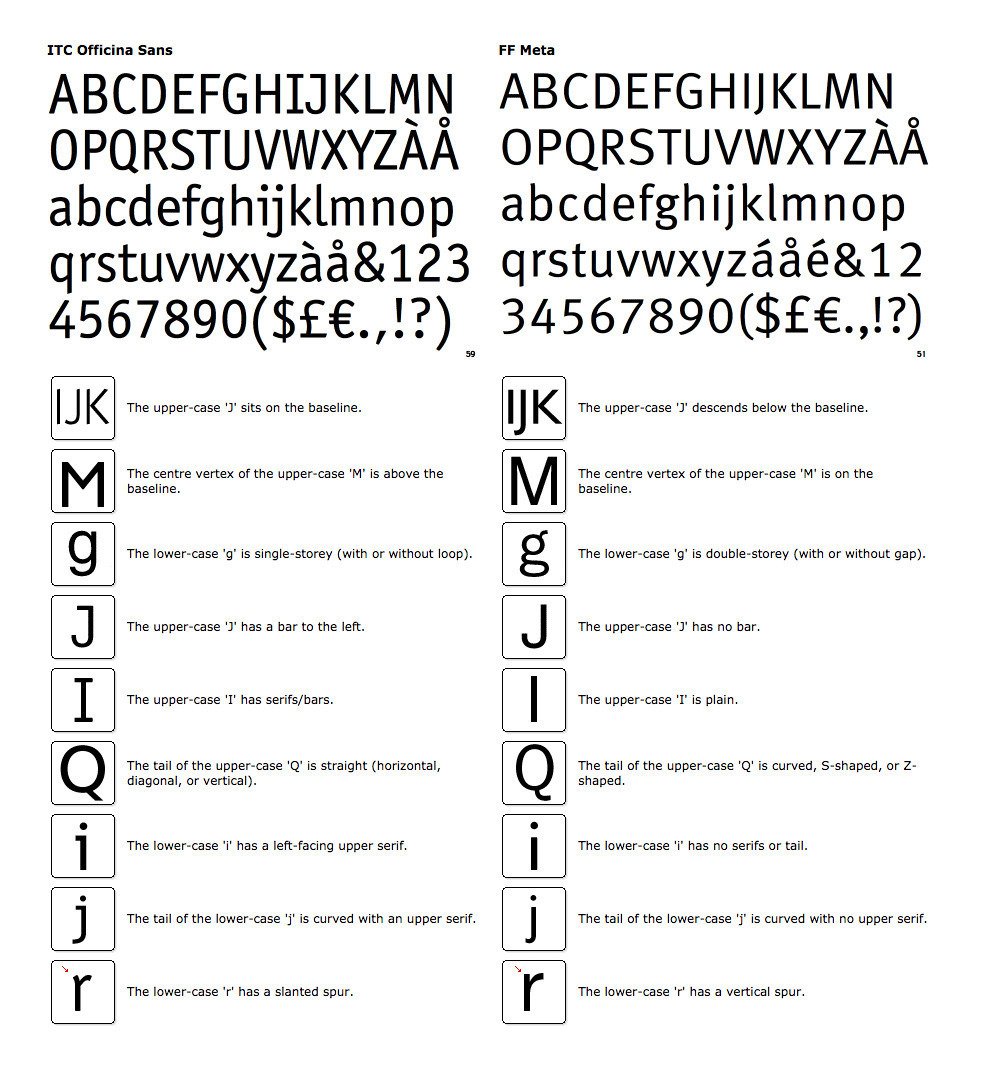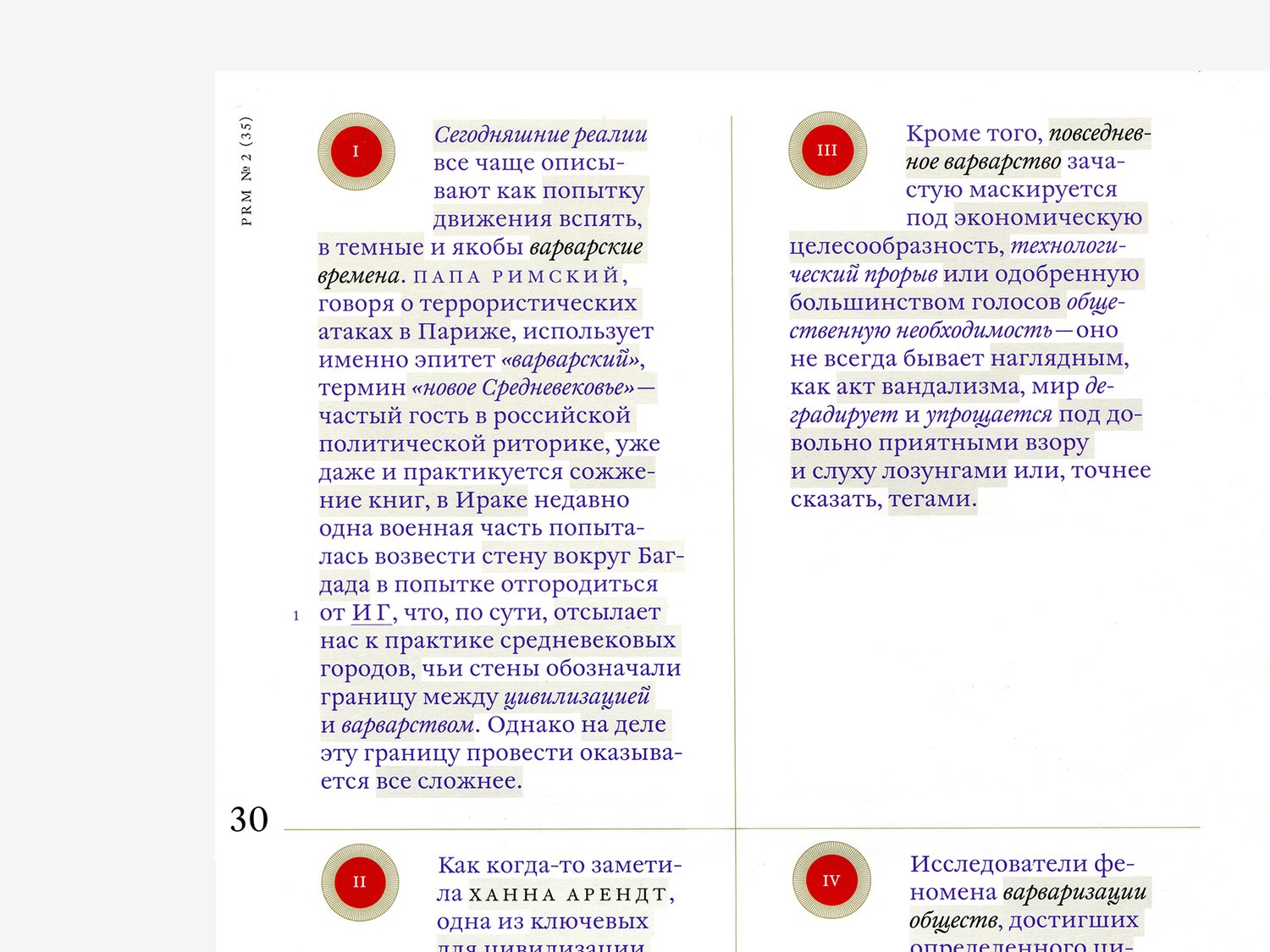
Shuka — одна из самых ярких дизайн-студий страны. Мы поговорили с со-основателем студии Иваном Величко о современном состоянии графического дизайна, швейцарской крови и реальности.
Илья Рудерман: Что для тебя шрифт сегодня?
Иван Величко: Странное дело, но сегодня все вокруг говорят о шрифтах. Шрифт стал какой-то модной темой для обсуждения, а для многих молодых дизайнеров — просто каким-то мистическим космосом, магией. Но мне кажется, что весь этот шум мы сами и создаём, мы сами искусственно вывели эту тему в топ.
Я, честно говоря, не вижу тут какого-то отдельного предмета для долгого обсуждения. Шрифт для меня — это всё-таки прежде всего инструмент. Я сам этим инструментом постоянно пользуюсь, с удовольствием могу порассуждать — какой шрифт мне больше нравится, какой меньше и почему, но не стоит устраивать из этого дискуссии планетарного масштаба.
На мой взгляд, проблема современного графического дизайна состоит в том, что для него ещё не придумали адекватного языка. Взять, например, другие профессии: в кино последние полвека все лучшие фильмы снимаются о том, как делать фильмы; театральные спектакли ставятся о том, что такое театр в наше нелёгкое время. А дизайн этой рефлексии избежал, у нашей профессии пока не появилось собственного понятийного аппарата. Поэтому всерьёз об этом рассуждать мы не умеем, у нас просто пока нет терминов.
ИР: Ты начал с того, что шрифт, в общем-то, микроскопическая история, недостойная серьёзного обсуждения, а закончил тем, что на самом деле проблема в отсутствии словаря для обсуждения графического дизайна и шрифтов. А как сегодня твоё общение со шрифтом — его использование и восприятие — отличается от того, что было, допустим, два года назад?
ИВ: Мой дизайн очень сильно связан с тем, из чего я его делаю. В своих работах мы часто используем то, что сами рисуем, графику, произведённую если не в стенах студии, то нашими друзьями или художниками, с которыми мы работаем. Шрифт — это большое количество чужой графики в макете, очень много графики, нарисованной каким-то другим художником. Много просто по площади, которую этот элемент занимает. И эта чужая графика очень сильно влияет на интонацию произведения, на то, как ты это делаешь, на то, как тебе с этим работается. Есть шрифты, с которыми нужно находить общий язык, есть шрифты, с которыми тебе просто некомфортно, есть шрифты, которые тебе ниспосланы провидением.
Сайт дизайн-бюро «Щука». На сайте используется специальная версия шрифта Gerbera вместе с безымянным гротеском Ивана Величко
Сайт дизайн-бюро «Щука». На сайте используется специальная версия шрифта Gerbera
У меня был опыт работы с Судостроительным банком («СБ Банк»). Они пришли и к нам в 2008 году со словами: «Наш фирменный шрифт — Officina». В 2008 году Officina выглядела анахронизмом из 2001 года. И я подумал: какой ужас, придётся иметь дело со шрифтом Officina. Однако поработав с ним какое-то время, я понял, что из него, вообще-то, можно вытащить совсем другие свойства, не те, что вытаскивали создатели брендбука в ранние 2000-е. Я придумал, как с ним сделать вполне модернистские композиции, как превратить его в модную историю.
ИР: С каким модным шрифтом тебе было некомфортно работать?
ИВ: С Meta. С «Метой» было сложно ещё и потому, что у него много начертаний. А по моим ощущениям, у шрифта есть ровно одно начертание, с которым мне комфортно, все остальные мне просто не нужны.
Сравнение шрифтов Officina Sans и Meta на сайте Identifont
Например, сейчас мы набрали сайт шрифтом Gerbera, который сделала Гаянэ (Гаянэ Багдасарян и Вячеслав Кирилленко — авторы шрифта Gerbera. — Прим. ред.), но мне для этого пришлось потрудиться, я везде поставил альтернейты, какие мне хотелось, попросил Гаянэ сделать специальный файл, и мы использовали только Medium.
ИР: Твои представления о шрифте по дефолту как-то менялись? Например, у тебя был период любви к одному шрифту, потом ты увлёкся другим? И какой дефолтный шрифт у тебя сейчас?
ИВ: Когда мы начинали делать многостраничные издания, у нас по дефолту стоял Charter, почти всегда. После Charter мы стали везде ставить William, который мой шрифт по умолчанию до сих пор.
Дизайн журнала The Prime Russian Magazine со шрифтом William
ИP: Мне нравится, что у тебя шрифты по дефолту — антиквы. А какой-нибудь гротесковый дефолт есть?
ИВ: Раньше я ставил Circe, они с «Вильямом» хорошая пара. Есть, правда, ощущение, что с Circe сегодня в городе небольшой перебор. И он сложноват для дефолтного шрифта. Но сейчас у меня новый любимый гротеск — Figgins.
Шрифт Figgins Sans дизайнера Ника Шина (Nick Shinn)
Чехословацкий трёхтомник Олдрича Главса (Oldřich Hlavsa) Typographia 1 (1976), Typographia 2 (1981), Typographia 3 (1986)
То, что вы сделали в «Казимире», эти старостильные знаки — это часть идентичности проекта, которой совсем не каждому придёт в голову воспользоваться.
ИР: Но тем не менее альтернативный комплект знаков «Казимира» используется очень часто. Оказывается, что некоторые его покупают именно из-за этого набора.
ИВ: Это классно, потому что это расшатывает границы допустимого, что очень правильно. Мне кажется, это общая цель нашей работы — расшатывать реальность.